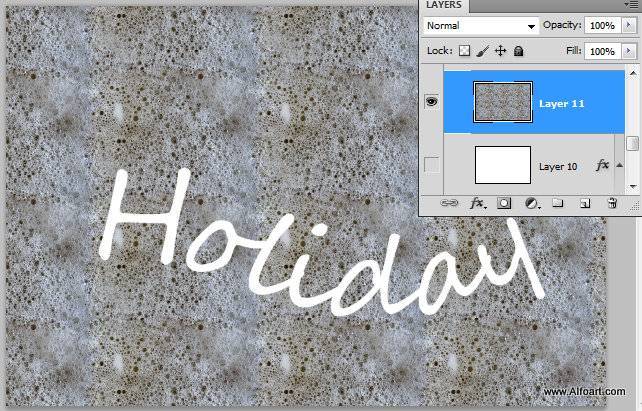
Подробный гайд по созданию серебристого текста в Фотошопе от профессионалов
Желаете научиться создавать эффектный серебряный текст в программе Adobe Photoshop? Этот гайд покажет вам подробные инструкции и советы от опытных дизайнеров, чтобы вы могли легко воплотить свои творческие идеи в реальность.
Выберите подходящий шрифт и размер для вашего текста. Рекомендуется использовать шрифты с максимальным контрастом, чтобы создать более яркий и эффектный серебристый эффект.
Примените эффект Объёмное свечение к вашему тексту. В настройках эффекта, выберите серебристый цвет и настройте параметры, чтобы достичь нужного финального результата. Играя со значениями затемнения и размытия, вы можете достичь различных текстур и глубин эффекта.
Для усиления эффекта серебряного текста, добавьте дополнительные элементы дизайна, такие как тени, перекрывающие текст или градиенты. Это поможет придать вашему тексту больше глубины и объема, делая его еще более выразительным.